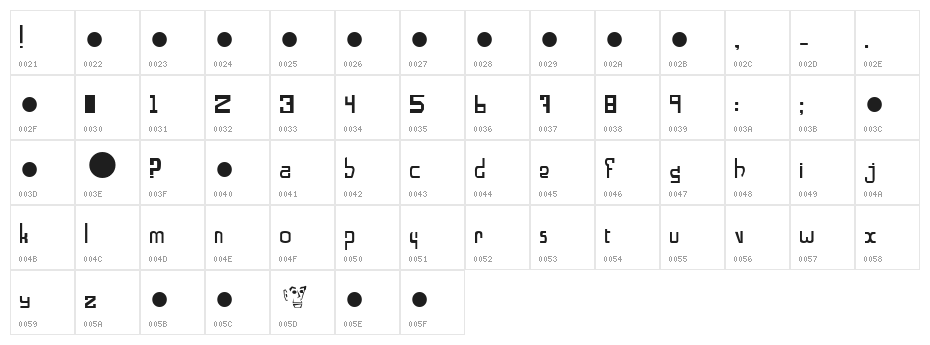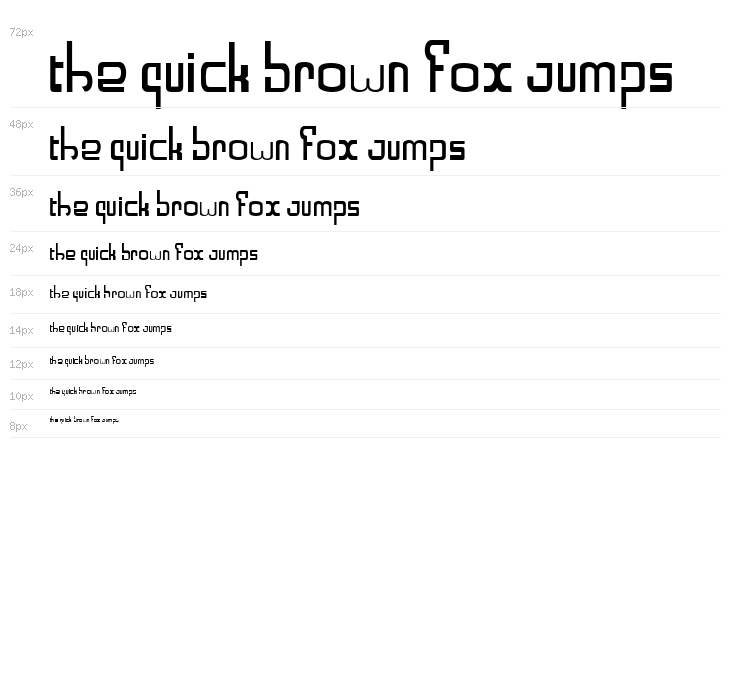
Alphabeta Font
| Estilo general | Modern, Futuristic |
| Caso de uso | Logos, Headlines, Digital interfaces |
| Proyectos propuestos | Ideal for technology branding, digital interfaces, video game design, and futuristic posters. |